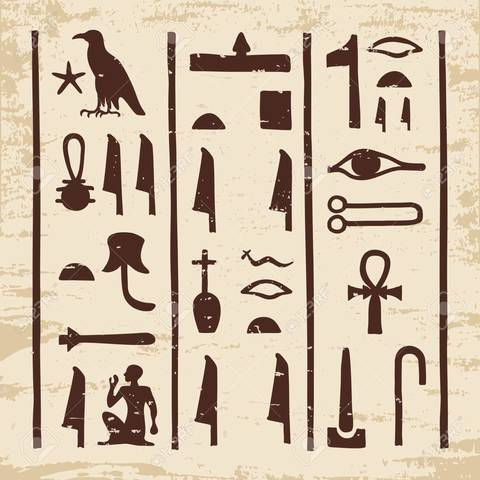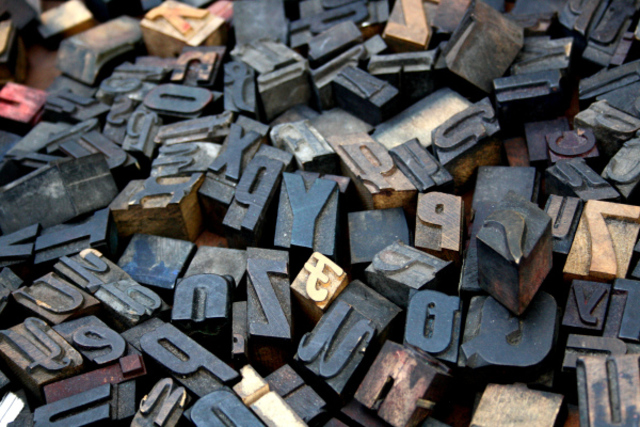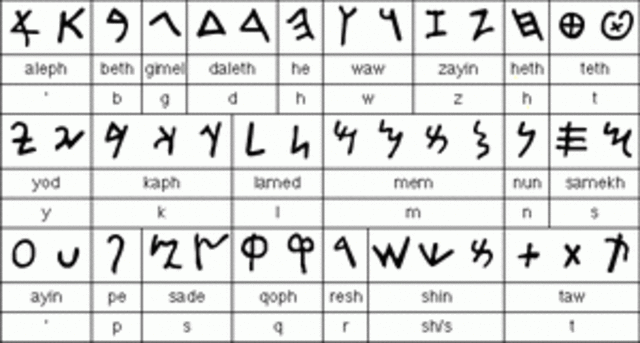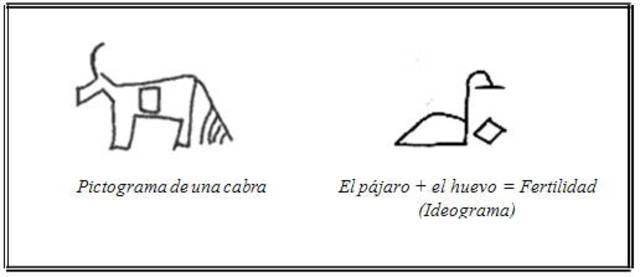
Nuestros antepasados nos legaron sus primeras ideas e impresiones sobre la escritura por medio de manifestaciones pictóricas.
El hombre del paleolítico superior para comunicarse utilizaba las imágenes, por medio de dibujos que pinta o graba sobre piedras o pieles.
Una de las escrituras demográficas mas importantes
Los sumerios inventaron un sistema de escritura que consistía en la utilización de cuñas que permitían grabar signos sobre tablillas de arcilla blanda las cuales se endurecían en un horno.
La comunicación a través de imágenes cambia del pictograma al ideograma que señala el comienzo de la historia de la escritura
Los primeros en escribir las consonantes aisladas fueron los pueblos semíticos occidentales de las orillas del mar Rojo y Mediterráneo, hebreos y fenicios,
Las formas más antiguas se encontraron en las inscripciones arcaicas de Biblos, 22 letras, consonantes, derecha a izquierda. Los primeros alfabetos fenicios se han encontrado en localidades de los actuales países de Líbano y Siria. Alfabetos cuneiforme y lineal.
Empleaban un silabario para la escritura entre los siglos XVI y XII a.C. Entre 1000 y 900 a.C adoptaron la variante fenicia del alfabeto semítico y a sus 22 consonantes añadieron dos signos. Utilizaron signos fenicios que no les eran útiles para notar también las vocales. Después de 500 a.C ya se escribía de izquierda a derecha. De él surgieron otras escrituras como la etrusca, osca, umbra y romana.
Los primeros caracteres chinos considerados en buena medida maduros son las inscripciones en huesos de animales y caparazones de tortugas denominadas Jiagu Wen de la época Yingshang
Los griegos adoptaron el sistema fenicio modificándolo conforme a sus necesidades al añadirle vocales y darles nombre a las letras.
Península itálica (El norte) a finales del octavo siglo a.C deriva del griego y fenicio.
tiene tres periodos: el arcaico, el clásico y el nuevo o postclásico.
Hebreo antiguo aparece en la época de los Reyes (Saúl, David, Salomón),
Unas de las escrituras ideograficas mas importantes
Alfabeto latino.
• Romano: lo adoptaron de los etruscos.
• Arcaico: La letra Z dejo de usarse y se cayo del alfabeto tomando su posición la letra G.
• Clásico: Se reintrodujo la Z y se adoptó la Y. -
El emperador de china pidió que se tallaran en piedra algunas obras del confucianismo.
Unciales.
Los griegos desarrollaron un estilo de escritura mas redondo llamado uncial , esta escritura se podría escribir mas rápidamente porque sus letras redondeadas se hacían con menos trazos. -
Parece ser la del aparato inventado por el chino Bi Sheng
Bloques de madera tallados y embadurnados con tinta, utilizados principalmente para reproducir imágenes religiosas.
Lauren Coster de Haarlem, en los Países Bajos, inventó los tipos móviles
Se atribuye a Gutenberg
Gutenberg desarrollo un sistema de tipos móviles independiente
El mayor trabajo que realizó Gutenberg con su imprenta fue la Biblia de 42 líneas. De 1450 a 1455.
Tras años de experimentación, logró poner a disposición de la humanidad uno de los mayores inventos de la historia: la Imprenta de tipos móviles de metal.